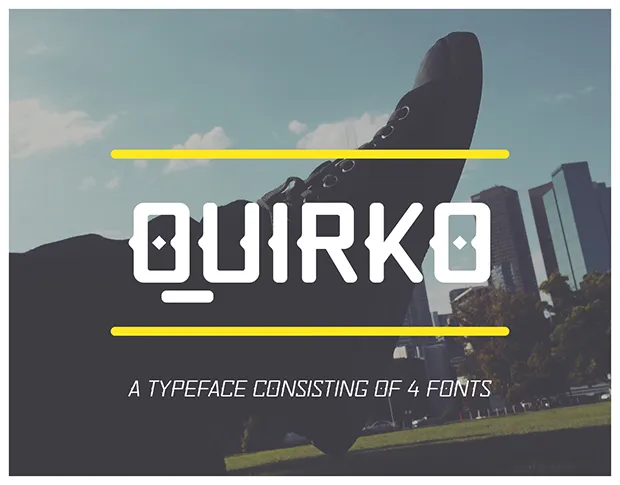
Quirko é uma família de 4 tipos de fontes inspirada em títulos serifados curtos e arredondados. Inspirado na elegância dessas formas, esta família oferece uma experiência visual única. A presença de estruturas triangularmente arredondadas, assim como elementos de forma parecidos a diamantes em certos caracteres, criam um estilo deslocado que se destacará em qualquer mídia. Essa combinada com seu aspecto assertivo e múltiplas opções de pesos, torna Quirko uma fonte ideal tanto para o design digital quanto impressão. Cada fonte na família possui mais de 300 caracteres gerais. Em um futuro próximo, experimente a essência da Quirko no seu projeto!